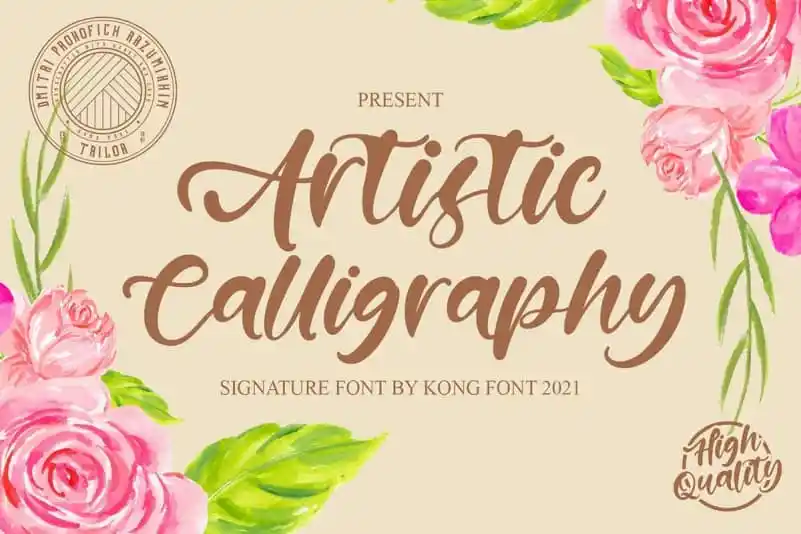
Artistic Script Font – Download Grátis
A Artistic Script Font é uma tipografia script com um ar contemporâneo que captura a essência do estilo clássico da escrita chinesa e japonesa, inspirada por tradições anteriores. Este tipo de letra apresenta uma forma perfeita, evitando excesso tanto na grossura quanto na finura dos traços, proporcionando um equilíbrio e variedade única em cada letra. Sua elegância está em constante mudança ao longo das linhas, oferecendo um aspecto que vai muito além de ser apenas uma fonte de escrita; ela é perfeita para criar textos chamativos e emotivos em qualquer tipo de projeto gráfico. A Artistic Script Font é o tipo de recurso essencial para designers e criadores digitais. Suas linhas fluidas, combinadas com nuances que a tornam única, permitem transformar um simples texto em uma obra-prima visual. A fonte se destaca como um complemento perfeito para trabalhos que exigem um toque de sofisticação e originalidade, seja em design gráfico, publicações digitais ou criações web.